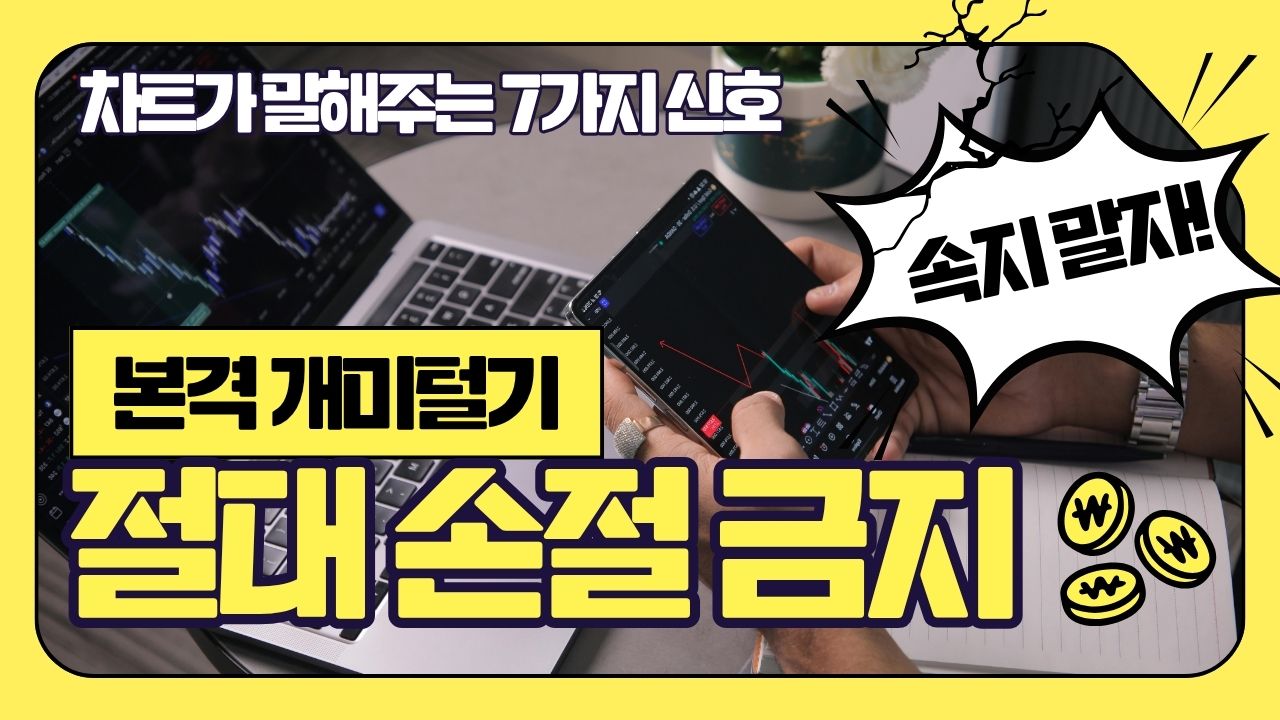
태나다체 무료폰트
태나다체 — 태나다에서 배포하는 무료 폰트입니다. 넓은 네모틀과 곧은 획에 스텐실 구조를 더한 독특한 제목용 서체
로고와 포스터를 만드는 앱 태나다가 배포하는 제목용 서체입니다.
조형에서 눈에 띄는 것은 스텐실입니다. 꽉 찬 네모틀 구조에 스텐실의 특징을 적용해 독특한 인상을 준다고 소개됩니다. 스텐실은 획이 중간에 끊긴 형태를 말하는데, 이 서체는 한글과 영문 모두 획이 만나는 부분에 그 절단면을 고르게 넣었습니다. 파일에서 재어 보면 자면을 넉넉히 채운 굵은 형태라 절단면이 더 도드라집니다.